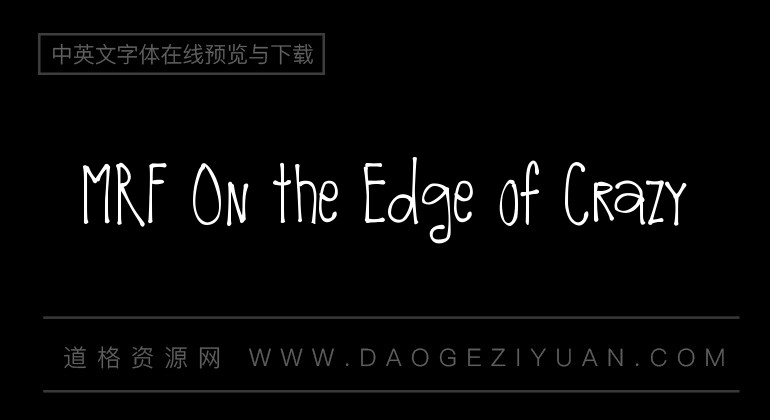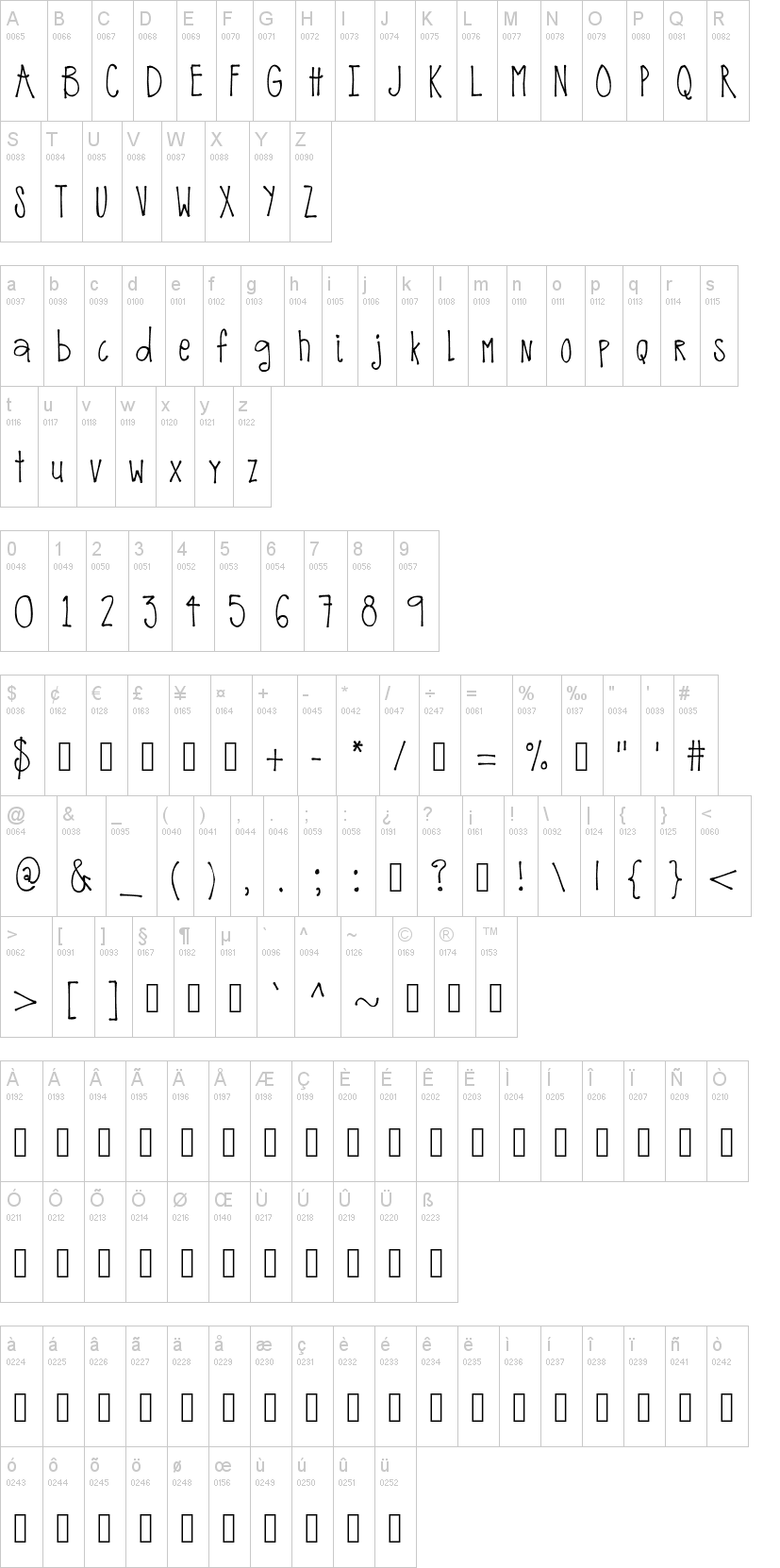
MRF On the Edge of Crazy是一款经典的字体,由MRF字体工作室设计,是一款优雅而抢眼的显示字体,具有极具特色的外观,可以用于制作海报、品牌标识、网页设计等等。它的特点是自然、简洁、优雅,具有独特的细节,可以让你的作品更加精致和出色。内容介绍
MRF On the Edge of Crazy是一款非常不错的手写艺术字体,具有很好的视觉感,适合于文化类的宣传设计、商业类品牌的广告和产品包装设计以及个性化文字排版等较多场景。